Aprende a elegir tipografías con Enric Jardí
Un maestro de la tipografía te enseña sus técnicas y secretos para elegir y combinar tipografías como un experto.
Si alguna vez te has propuesto intentar entender una señal o un cartel de un idioma que desconoces, probablemente te habrás dado cuenta de una cosa. Las letras hablan y cuentan mucho más allá de lo que dicen las palabras que se escriben con ellas. Las tipografías son capaces de mostrarnos cierta información sobre el tipo de texto que están queriendo mostrar y por eso es esencial saber utilizarlas adecuadamente. Enric Jardí (@enricjardi) es especialista en comprender la idiosincrasia de la tipografía y nos enseña cómo mejorar nuestros diseños gracias a ella en su curso Cómo elegir tipografías.
Enric Jardí lleva media vida dedicado a la gramática de las imágenes, explorando las posibilidades comunicativas y expresivas de las tipografías, desgranando el significado de las palabras y la forma de las letras para encontrar la mejor manera de hacer que la tipografía hable por sí misma. En los 90 fundó Type-Ø-Tones, un colectivo de diseñadores apasionados por la tipografía y el diseño de letras, junto a Joan Barjau, Laura Meseguer y José Manuel Urós.
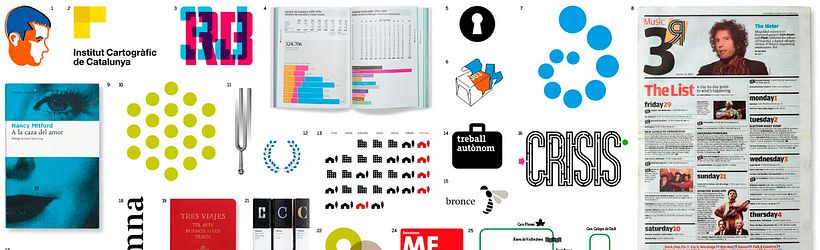
Su manera de entender la tipografía es diferente, por eso en este curso se aleja de la dogmática habitual de los libros de texto, que se detienen en los aspectos formales de las letras, para centrarse más en el significado de la tipografía, en las metáforas que esconde el lenguaje y en la mejor manera de combinar los tipos de letra para que nuestros diseños hablen de lo que queremos que hablen.